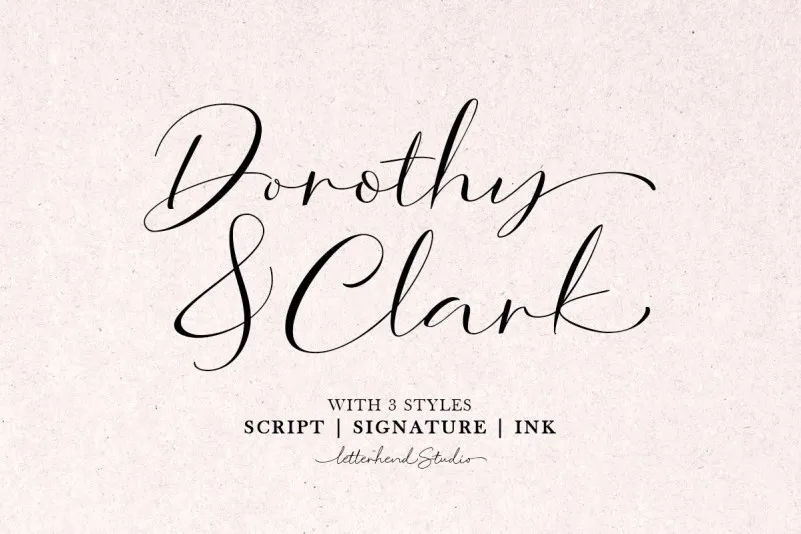
Dorothy Clark Script Font – Download Grátis
Introduzimos a Dorothy Clark Font. Trata-se de uma fonte moderna inspirada na calligrafia, escrita à mão sob o impulso da calligrafia moderna. Esta fonte cria um aspecto luxuoso e elegante nas designações. Foi criada pelo Letterhend Studio. O estilo desta fonte apresenta três formatos distintos: script regular, script de assinatura e script de tinta. Esta tipografia inclui uma funcionalidade OpenType única, que pode ser observada na segunda imagem do preview. A Dorothy Clark Font é perfeitamente projetada para aplicação em logotipos e outras formas formais como convites, rótulos, logos, revistas, livros, cartas de cumprimentos ou casamentos, embalagens, moda, maquiagem, itens de papelaria, livros, rótulos ou qualquer propósito publicitário. Essa fonte certamente se destaca em seus designes formais e elegantes.